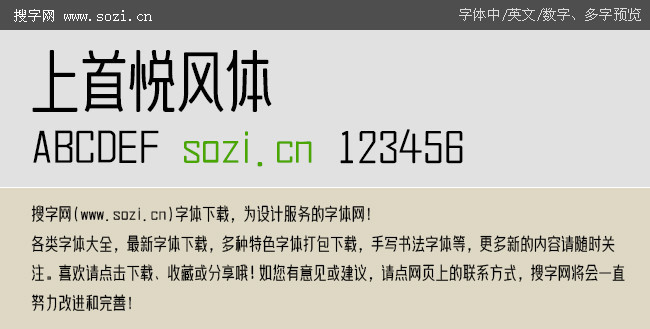
上首悅風(fēng)體
搜字網(wǎng)給大家提供一款上首悅風(fēng)體中文字體下載,上首悅風(fēng)體是上首字庫推出的一款非常精致的藝術(shù)字體,字體筆畫圓潤,橫豎筆進(jìn)行了簡化,整體導(dǎo)圓處理,字體修長,具有古典風(fēng)格?蓱(yīng)用于各類報紙、雜志、海報、包裝等廣告設(shè)計。